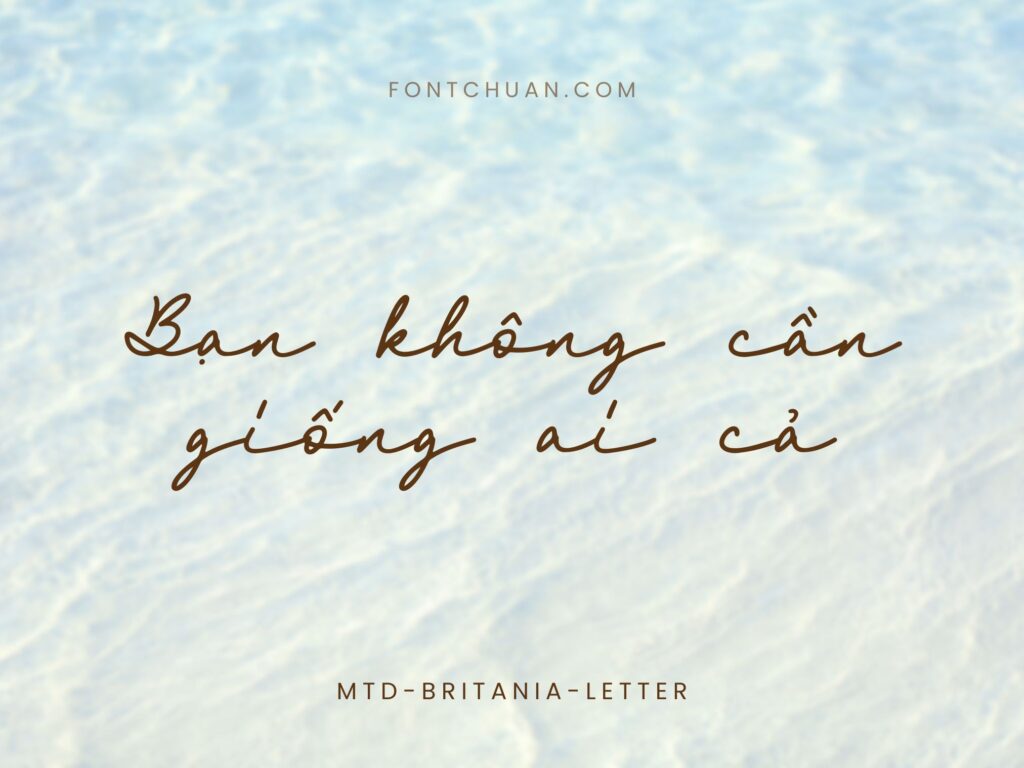
Font MTD Britania Letter Việt Hóa
Tác giả Font: Runsell Studio
Britania Letter là một font chữ ấn tượng được thiết kế bởi Runsell Studio, mang phong cách cổ điển kết hợp với sự hiện đại. Với các đường nét mềm mại và tinh tế, font này giúp tạo ra cảm giác thanh lịch và chuyên nghiệp trong các thiết kế sáng tạo. Để hỗ trợ cộng đồng thiết kế Việt Nam, Mộc Hạ đã Việt hóa font Britania Letter, giúp font này hỗ trợ đầy đủ tiếng Việt cùng hơn 200 ngôn ngữ khác. Phiên bản Britania Letter Việt hóa đã được thành viên Font Chuẩn sưu tầm và đăng tải, nhằm mang đến sự lựa chọn phong phú hơn cho các nhà thiết kế.
Về đặc điểm thiết kế, Britania Letter sở hữu những ký tự có đường nét mượt mà và độ tương phản nhẹ, tạo sự tinh tế trong từng chi tiết. Font này rất phù hợp với các thiết kế thương hiệu, thiệp cưới, typography nghệ thuật và bao bì sản phẩm. Ngoài ra, Britania Letter cũng là một lựa chọn lý tưởng cho các ngành nghề như quảng cáo, giáo dục và ẩm thực, giúp mang lại phong cách sang trọng và tinh tế. Font này cũng rất thích hợp để sử dụng trong các sự kiện như Valentine, Sinh nhật và các lễ hội.